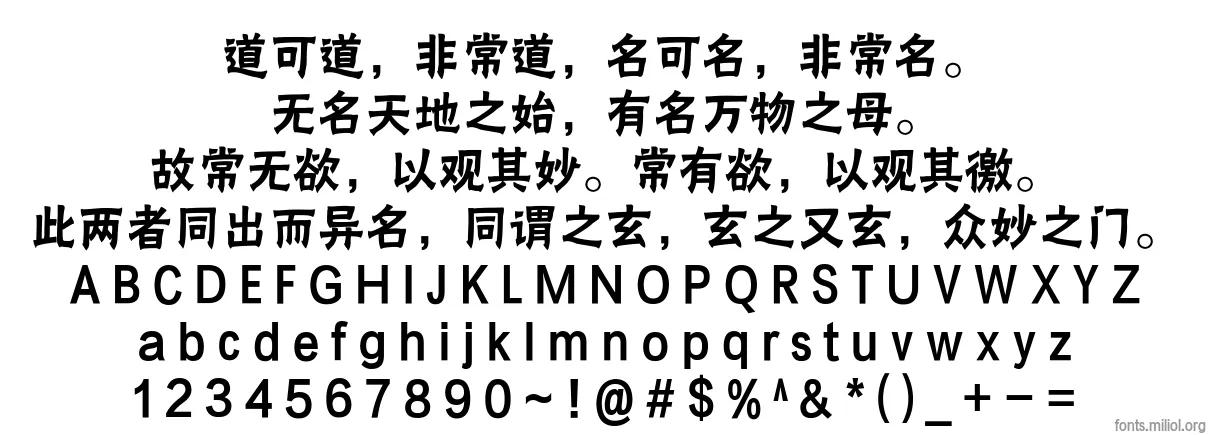
方正艺黑_GBK (FZYiHei-M20) (FZYHK--GBK1-0) 字体下载
方正艺黑_GBK是一款极具设计感的黑体字体,字形简洁大方,适用于标题、广告、海报等多种设计场景。其独特的艺术风格与GBK编码的广泛兼容性,使其成为设计师和排版工作者的理想选择。无论是印刷品还是数字媒体,方正艺黑都能为作品增添现代感和视觉冲击力。
方正艺黑_GBK 字体映射图